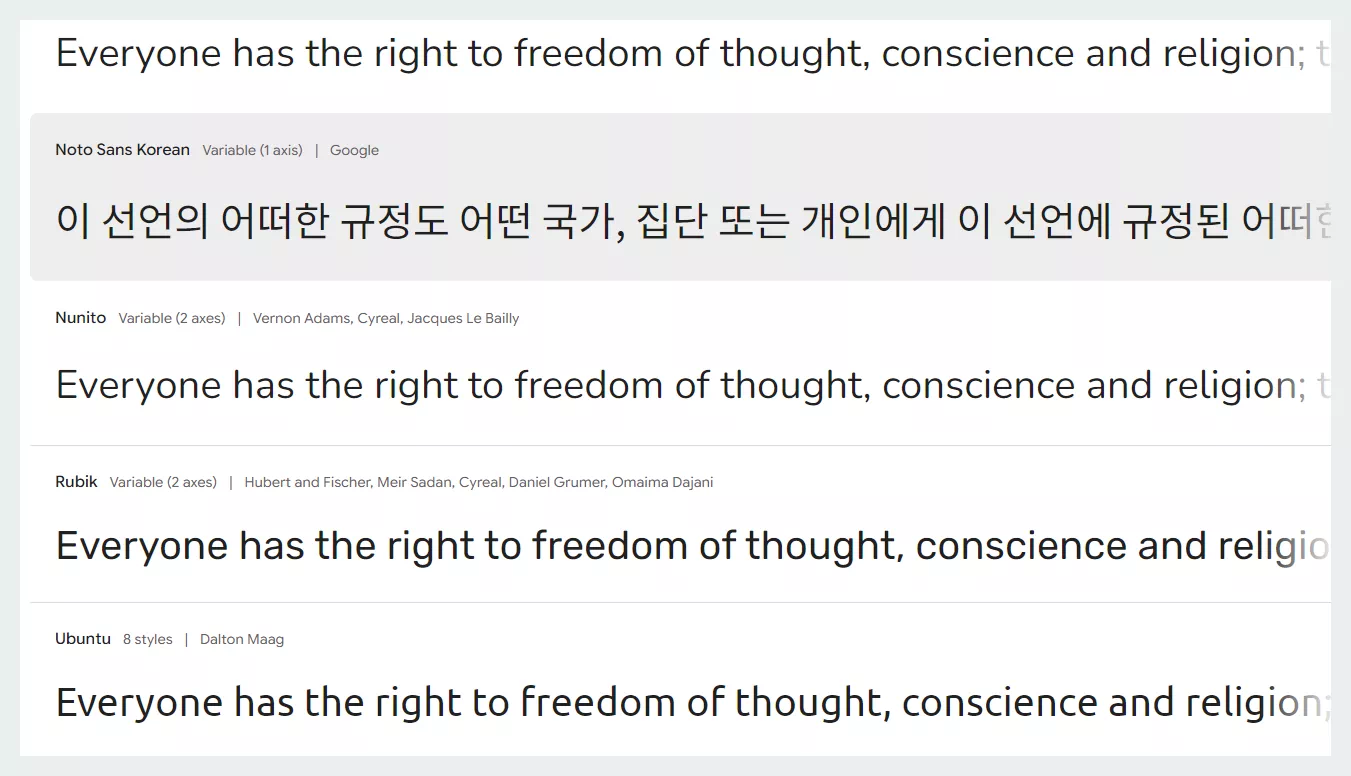
산세리프 폰트는 글자 끝에 장식적인 요소가 없는 깔끔한 서체로, 현대적인 디자인과 가독성을 강조합니다. 이번 글에서는 산세리프 폰트의 특징과 활용 방법, 그리고 무료로 다운로드할 수 있는 추천 사이트를 소개합니다.
산세리프 폰트란 무엇인가?
산세리프(Sans-Serif) 폰트는 글자 끝부분에 세리프(장식적인 선)가 없는 서체를 의미합니다. ‘산스(Sans)’는 프랑스어로 ‘없다’는 뜻이며, 산세리프는 ‘세리프가 없는 폰트’를 뜻합니다. 깔끔하고 현대적인 느낌을 주기 때문에 웹 디자인, 앱 UI, 브랜드 로고 등 다양한 분야에서 널리 사용됩니다.
산세리프 폰트의 주요 특징
- 세리프의 부재: 장식적인 선이 없어 글자가 단순하고 명확합니다.
- 높은 가독성: 작은 글씨에서도 선명하게 보이며, 디지털 스크린에서 특히 효과적입니다.
- 다양한 스타일: 기하학적, 인간적인, 중립적인 등 하위 분류가 많아 다양한 용도로 활용 가능합니다.
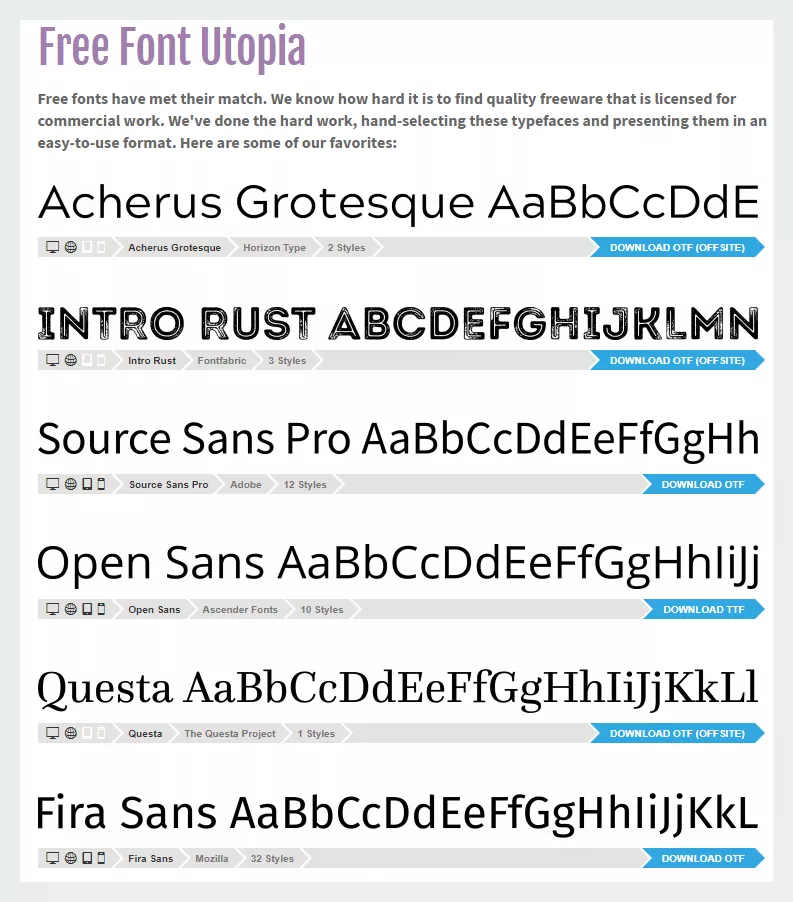
산세리프 폰트의 장점
산세리프 폰트는 단순히 디자인 요소로만 끝나지 않습니다. 다음은 산세리프 폰트가 가진 실질적인 장점입니다:
- 디지털 환경 최적화: 가독성이 높아 웹사이트, 앱 UI, 디지털 광고에 적합합니다.
- 현대적이고 세련된 느낌: 특히 IT, 테크 산업에서 자주 사용되는 이유입니다.
- 브랜딩에 적합: 글로벌 브랜드 로고에서 자주 볼 수 있는 깔끔한 서체입니다.
한글 산세리프 폰트의 매력
한글 산세리프 폰트는 ‘고딕체’로 불리며, 깔끔하면서도 세련된 느낌을 줍니다. 대표적인 한글 산세리프 폰트로는 나눔고딕, 스포카 한 산스, 프리텐다드 등이 있습니다.
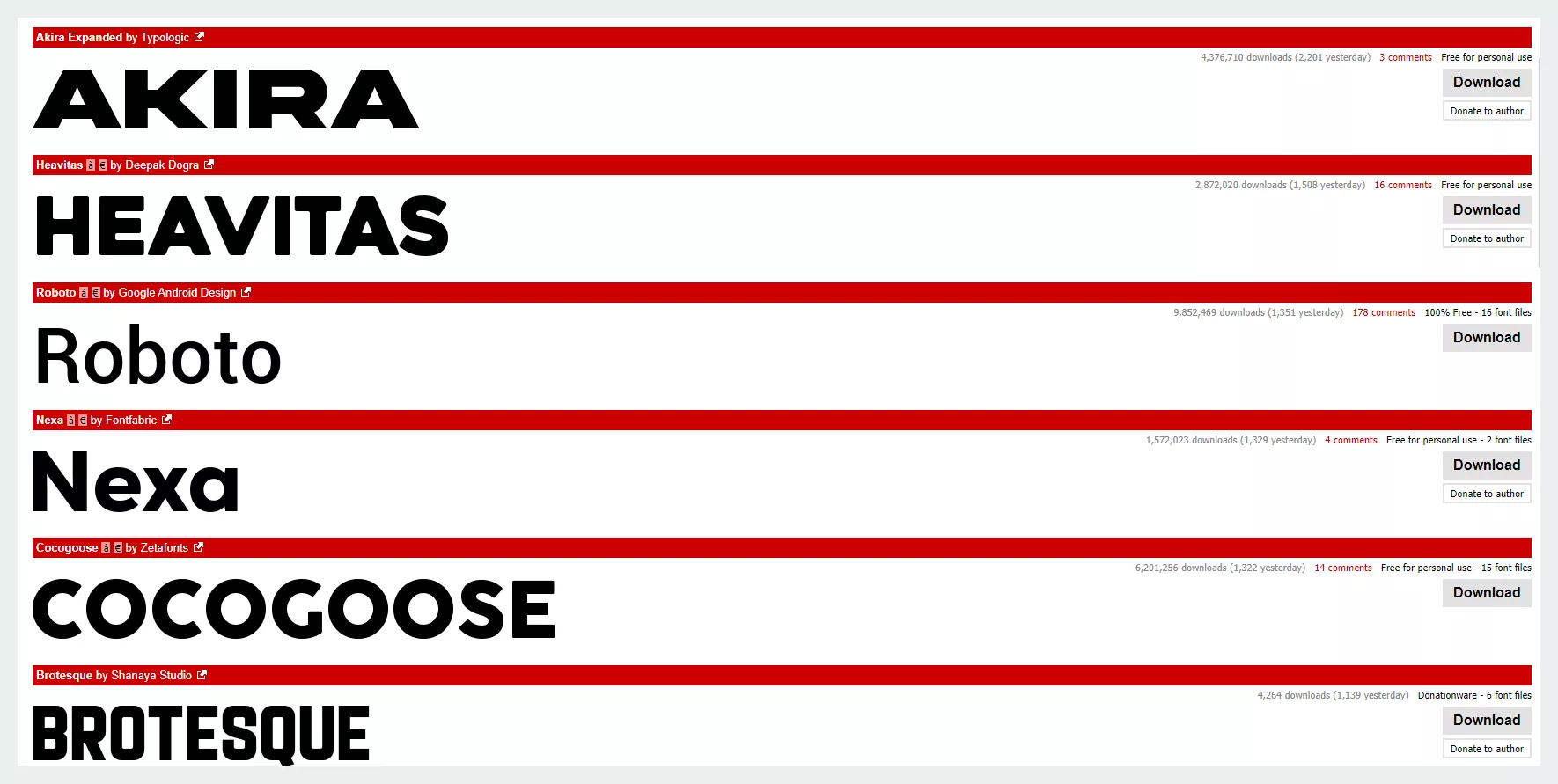
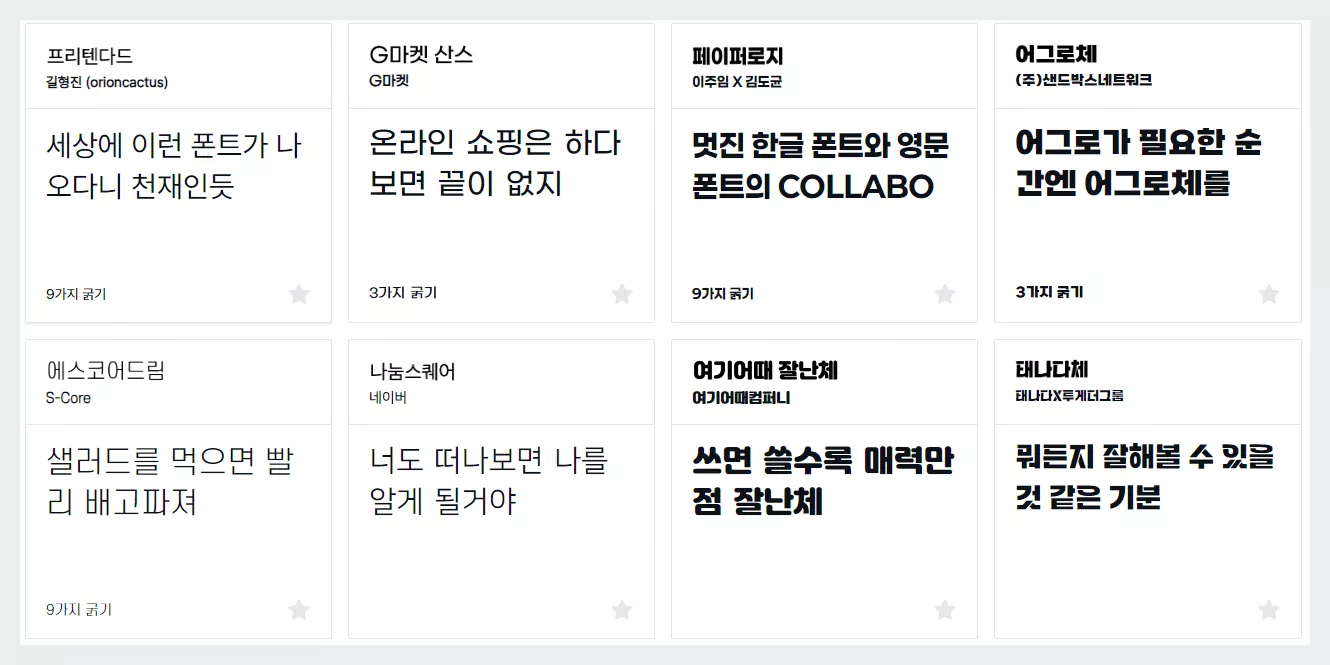
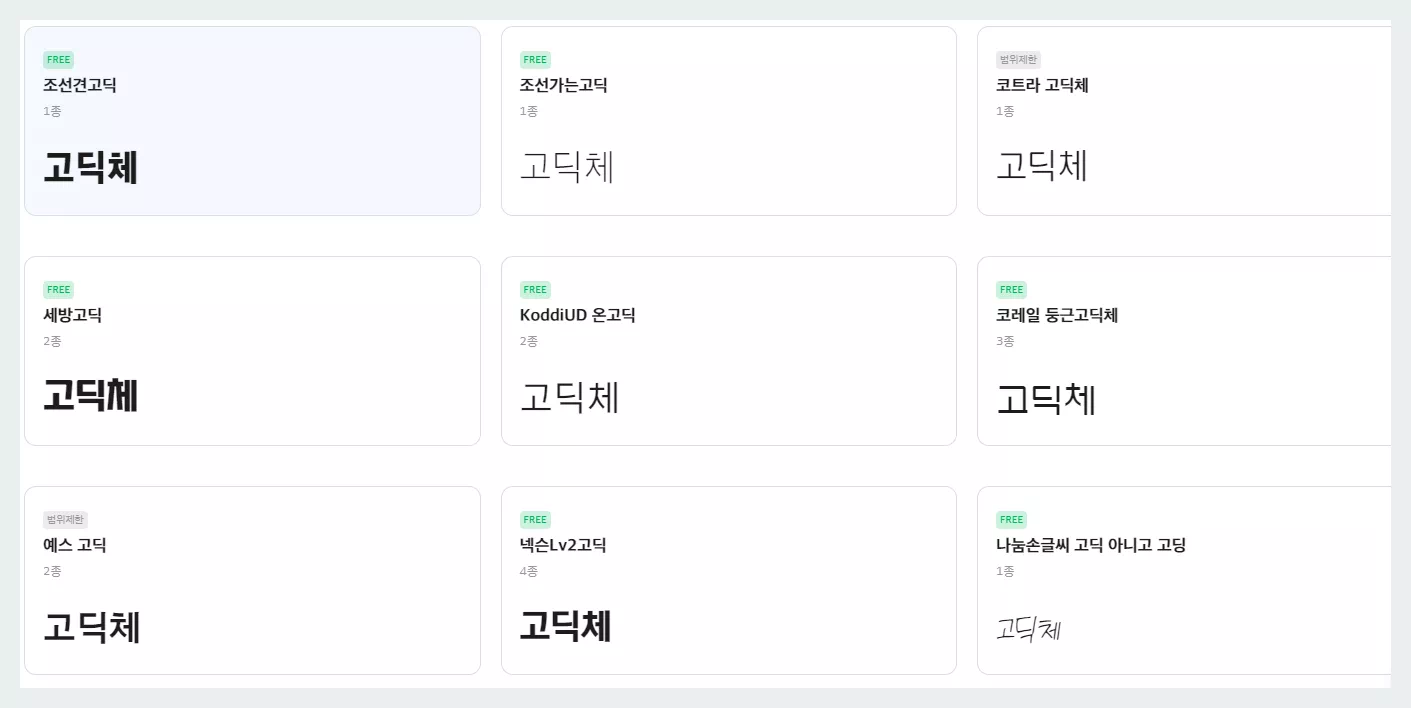
FAQ: 산세리프 폰트와 관련된 자주 묻는 질문
Q1: 산세리프 폰트는 어디에 사용하면 좋을까요?
A1: 산세리프 폰트는 웹사이트, 앱 디자인, 광고, 프레젠테이션 등 현대적이고 깔끔한 느낌이 필요한 모든 곳에 적합합니다.